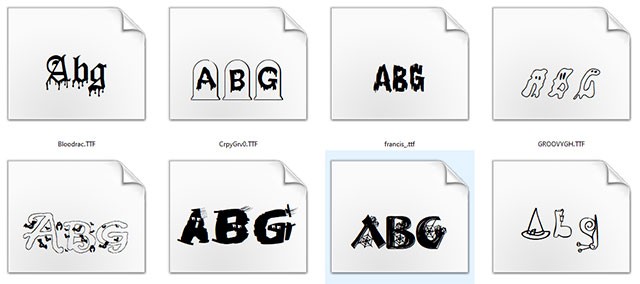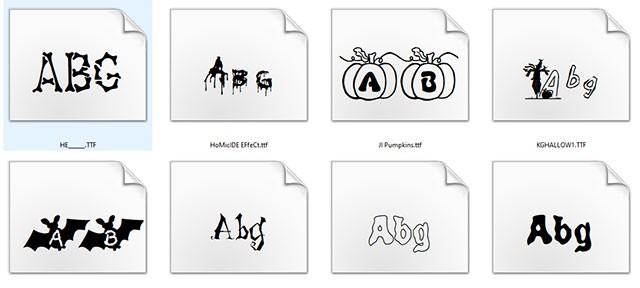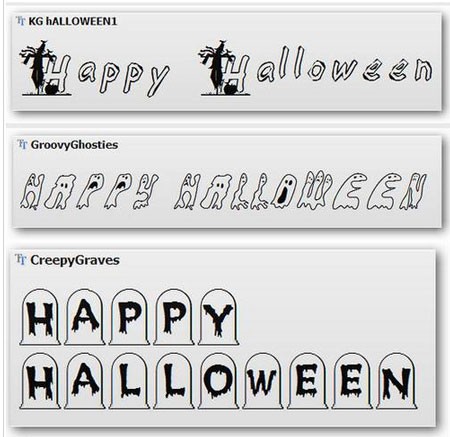
Khám phá Bộ Font Chữ Halloween Độc Đáo
Với font chữ Halloween, bạn sẽ sở hữu một bộ sưu tập các kiểu chữ viết nghệ thuật, mang đến vẻ đẹp mắt và độc đáo. Bộ phông chữ Halloween Fonts là một lựa chọn lý tưởng cho những ai muốn tạo ra các thiết kế liên quan đến lễ hội hóa trang. Chắc chắn, Halloween Fonts sẽ đóng góp không nhỏ vào thành công của ngày lễ đặc biệt này.
Cấu Trúc Bộ Font Chữ Halloween
Bộ chữ viết Halloween bao gồm 19 font chữ được thiết kế theo nhiều phong cách khác nhau, bao gồm cả chữ in hoa và chữ thường. Người dùng chỉ cần tải Halloween Fonts về máy, sau đó giải nén để bắt đầu sử dụng.
Những font chữ này được vẽ tay theo phong cách Halloween, lấy cảm hứng từ những bộ xương cổ đại và những con tàu cướp biển ma quái. Thiết kế của chúng vừa vui nhộn, nhẹ nhàng, vừa không kém phần rùng rợn, do đó rất phù hợp cho các thiết kế liên quan đến lễ hội này.
Vào ngày này, giới trẻ, đặc biệt là học sinh, sinh viên, thường tổ chức những buổi lễ độc đáo, hóa trang và trang hoàng không gian theo phong cách “rùng rợn” và đáng sợ. Với bộ font chữ Halloween dưới đây, bạn có thể sử dụng để chèn vào ảnh, card, v.v., nhằm tạo sự độc đáo cho ngày lễ hội.